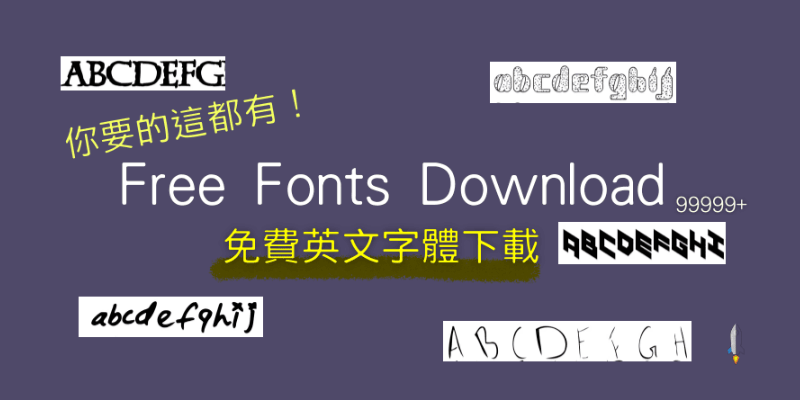
你要的字體都在這!可商用的Free Fonts download線上免費英文字體下載,多達20000個免費的英文字型,每天更新。能把字體套用到數字/標點符號/英文字上。
Free Fonts超過600+個免費英文手寫字體下載,可個人與商用!100%免費的高質感字體,有手繪風、草寫、簽名字體、筆刷等藝術風格的英文字型
UrbanFonts免費英文字型,可供個人使用、商業用(部分),無論是在找藝術字、希臘風、個性、草寫、連寫、手寫、打字機、襯字、書法、可愛英文字體…
FontSpace free fonts免費英文字體下載網站,提供超過6萬款可愛的、有個性的、襯字、特殊英文字體下載,可把字體安裝在Windows和Mac電腦上
Font Meme免費的英文字體網站,分享了不少常見的知名企業LOGO、電影、卡通、漫畫、兒童手寫塗鴉、動物裝飾等…充滿個性的特色字型。
BeFont幫大家整理了幾個好看的免費英文字體下載,手寫字體、書法、藝術字體、塗鴉風、英文可愛字體、高質感質感英文字體或是Logo字體通通有。